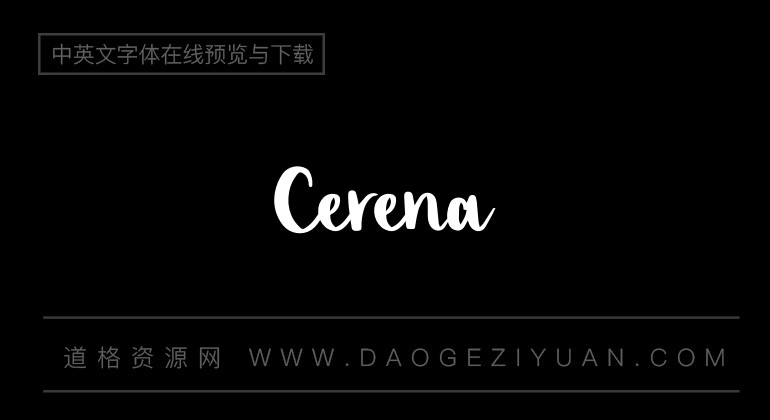
Cerena 字体是一种新的简洁舒适的护眼字体,它是一种新型的易读易写字体,可以有效减少眼睛的疲劳。它采用了特殊的字形设计,使字体更加清晰,更易于阅读,同时也更易于写作。Cerena字体的特点是拥有更宽的字符间距,允许更多的空间来显示字符,更大的字体大小,以及更多的字符组合。它的字体设计也更加简洁,使得内容更加容易理解。Cerena字体适用于所有类型的文本,可以提高文本的可读性,改善文本的可视性,并且可以有效减少眼睛疲劳。内容介绍
Cerena是一款非常不错的手写艺术字体,具有很好的视觉感,适合于文化类的宣传设计、商业类品牌的广告和产品包装设计以及个性化文字排版等较多场景。